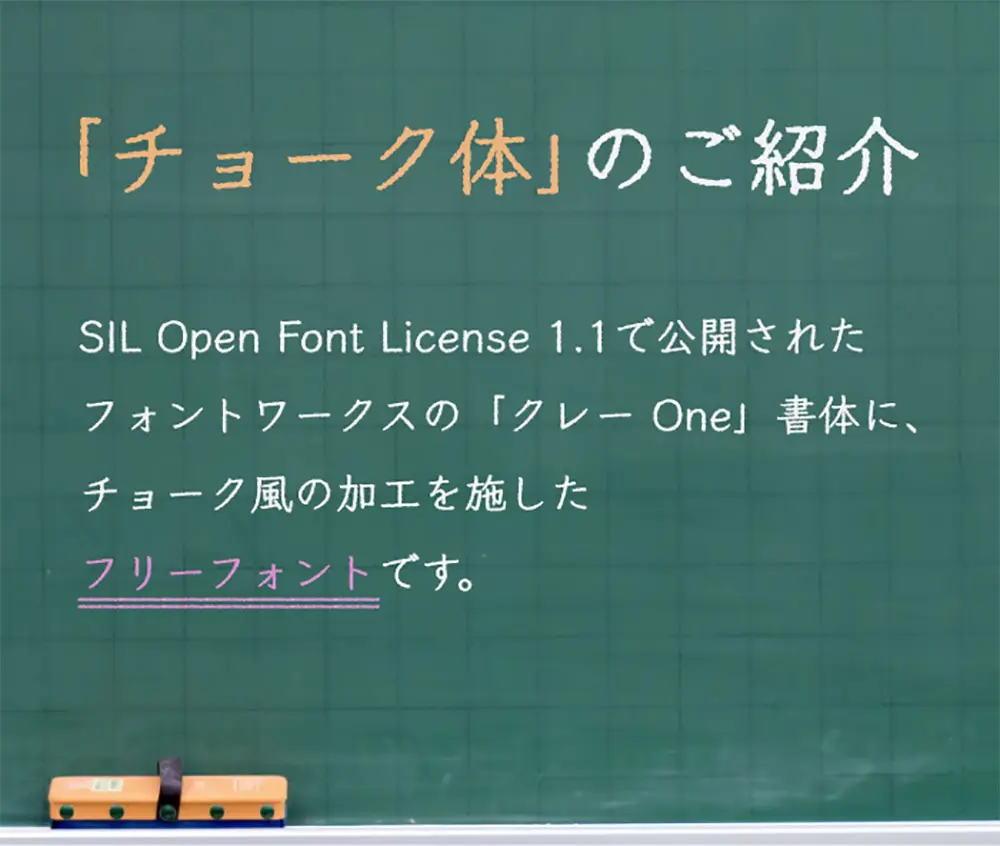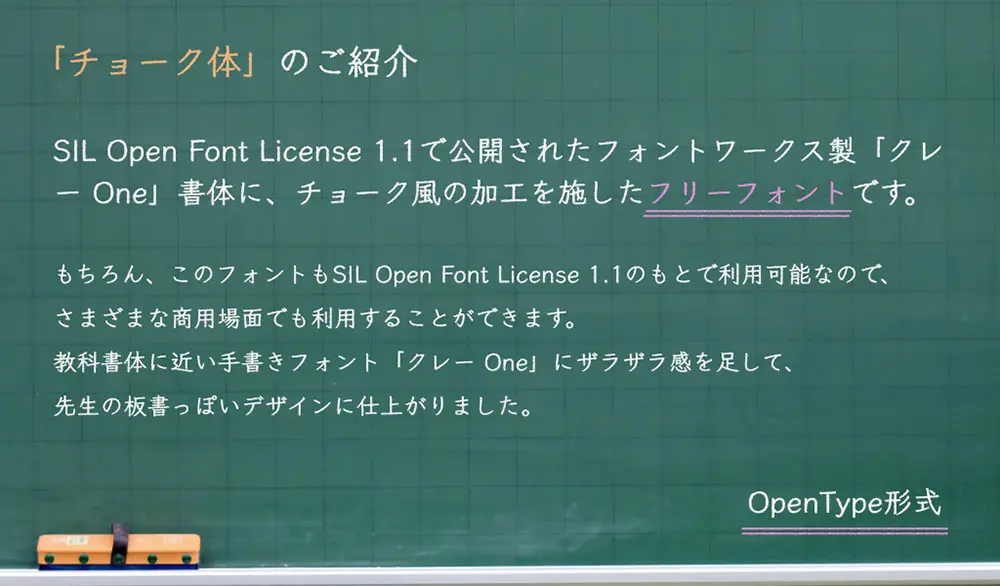
粉筆體(チョーク體)是一種免費的字體“粉筆體”,其設計看起來像是用粉筆寫在黑板上的。此字體是Fontworks製造的字體「Klee One(クレー One)」的修改版本,該字體採用SIL Open Font License 1.1發佈,通過一些處理,設計具有破損和粉筆般的感覺。
黒板にチョークで書いたようなデザインのフリーフォント「チョーク體」を公開しました。このフォントは、先日「SIL Open Font License 1.1」で公開されたフォントワークス社製の書體「Klee One(クレー One)」を改変したフォントです。いくつかの処理を加えることで、ザラザラ感のあるデザインになり、チョーク風の雰囲気に仕上がりました。